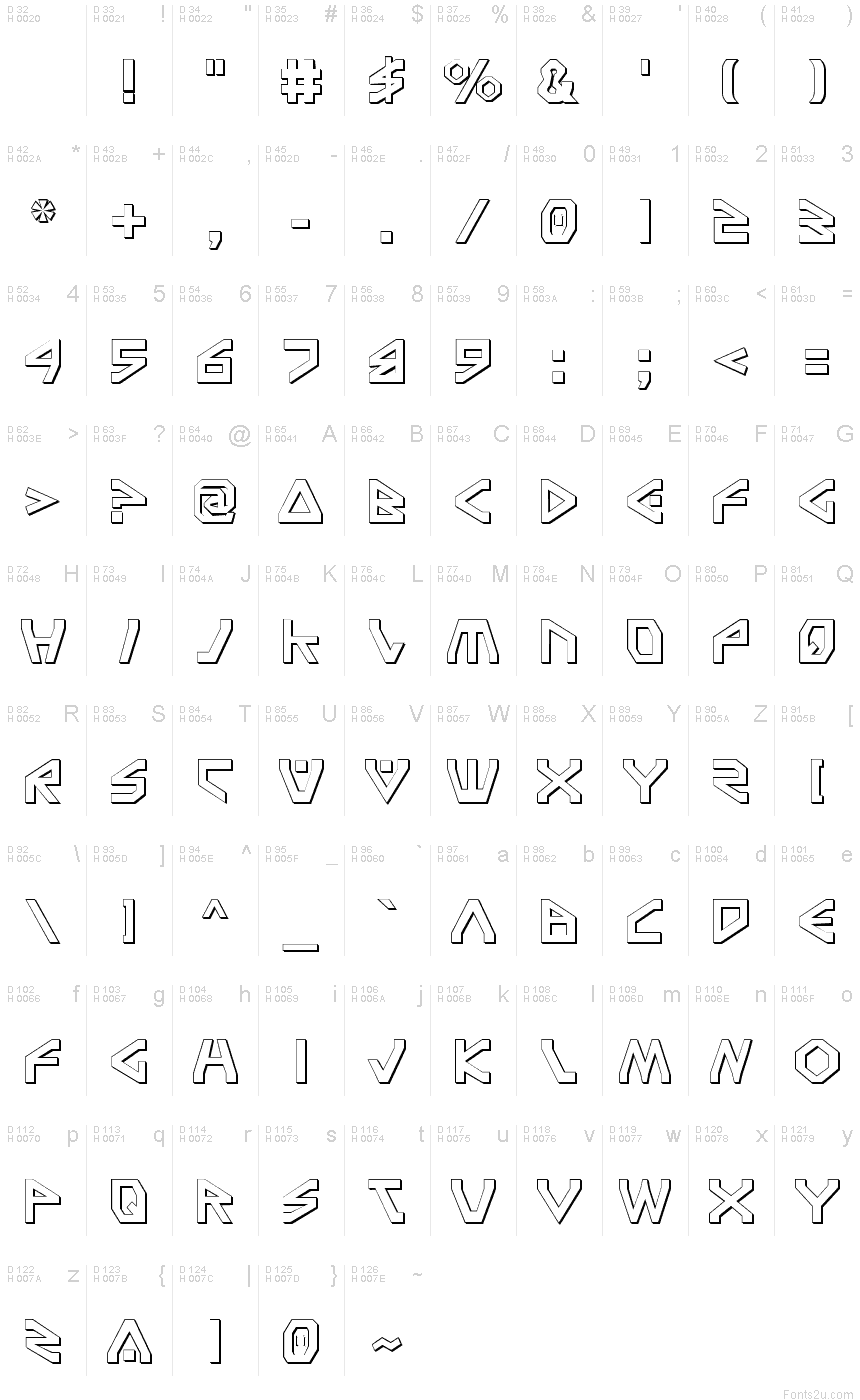
Terra Firma Shadow von Iconian Fonts ist eine kostenlose Techno-Schrift mit Schatteneffekt, deren scharfkantige Großbuchstaben wirken, als wären sie aus Metall geschnitten. Die Buchstaben bestechen durch harte Winkel, Ecken und einen versetzten 3D-Schatten, der der Schrift eine frische Sci-Fi- und Arcade-Stimmung verleiht, ohne überladen zu wirken.
Sie eignet sich hervorragend für Spiele-Logos, Poster-Überschriften, Titelkarten, Albumcover und E-Sport-Branding – überall dort, wo kurze Wörter den gestuften Schatten für sich sprechen lassen. Als kostenlose Schrift passt sie zudem perfekt zu Flyer-Überschriften, Stream-Grafiken und Monogrammen, wenn Sie einen geometrisch-mechanischen Look suchen, der nicht glattpoliert oder futuristisch wirkt.